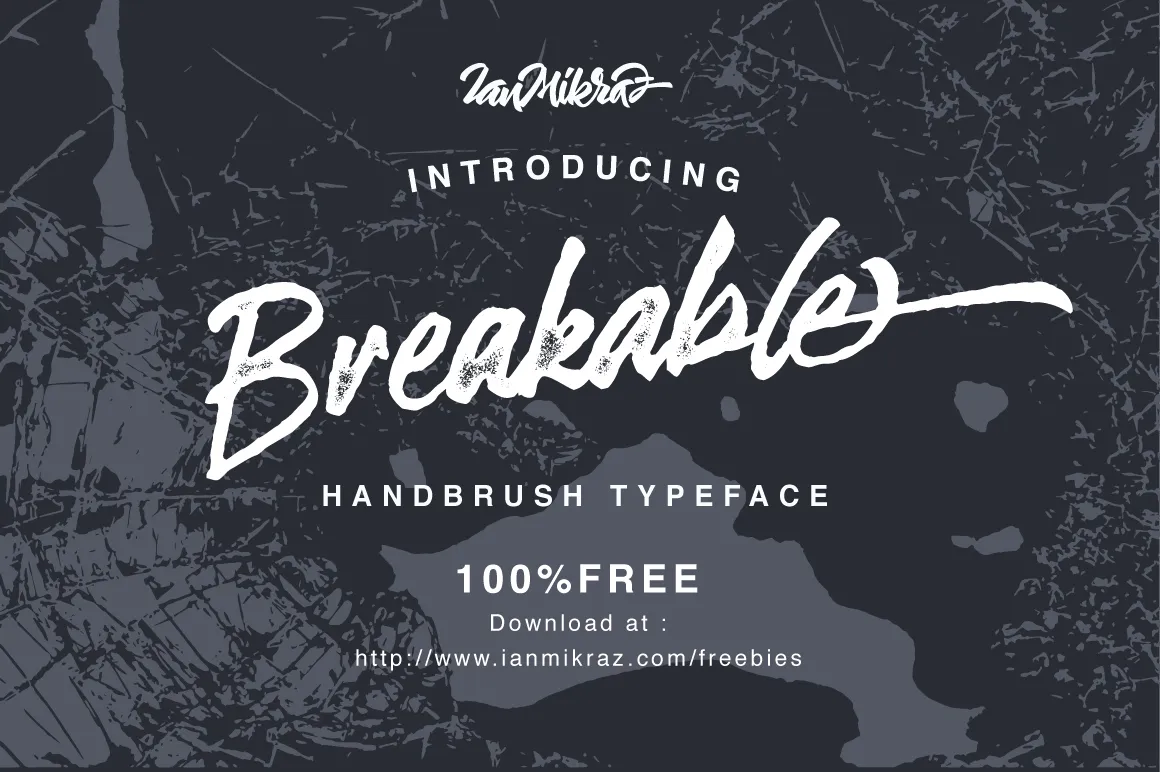
Aqui está uma descrição envolvente e natural para a página de download da fonte ‘Breakable Brush Font’ no português brasileiro: Estamos sempre buscando novas inspirações para nossos projetos gráficos? Então, você precisa conhecer Breakable Brush Font. Inspirada na arte livre e despojada do Ianmikraz Studio, essa fonte brush oferece uma nova experiência em estilo de letra manual. Ela une as características únicas da escrita a mão com o toque delicado dos pinceis, criando um resultado único e intrigante. Com 264 gílios e 85 alternativas de caracteres disponíveis, Breakable Free Typeface é uma coleção completa que oferece opções incríveis para personalizar seus projetos. Além disso, a fonte suporta funcionalidades avançadas como Alternativas Estilísticas, Ligatura de Prática e muito mais. Se você gosta de trabalhar com Adobe Illustrator ou InDesign, por exemplo, é perfeito para adicionar personalidade ao seu design. Essas alternativas permitem que você personalize ainda mais os caracteres, criando textos dinâmicos e interessantes. Seja para rótulos, identidades visuais ou qualquer outro projeto, Breakable Brush Font trará um toque único a seus designs. Descubra essa nova fonte brush de alta qualidade e adicione-a à sua coleção confiável de recursos gráficos. Você não vai se arrepender!